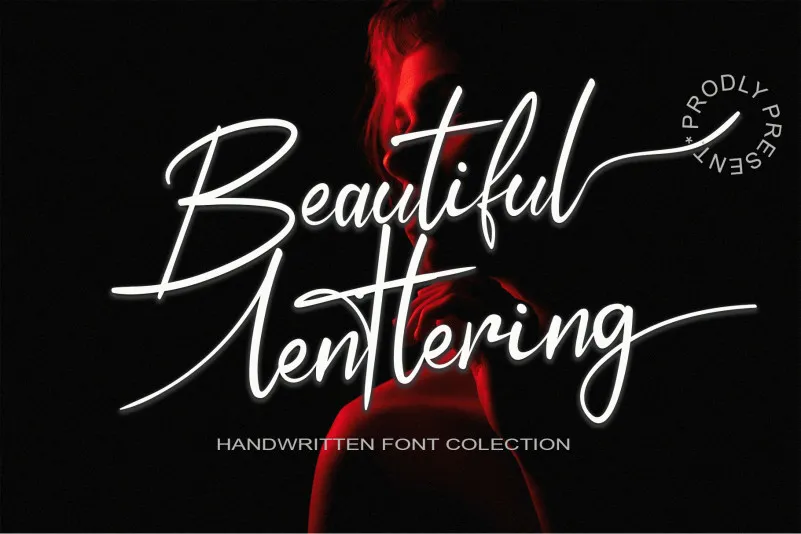
Beautiful Lenttering Font – Download Grátis
Esta é uma fonte script elegante com um clima contemporâneo e forma perfeita, inspirada em escrita clássica que resistiu ao tempo. Suave para os olhos, não é excessivamente fina nem grossa. Equilibrada e variada, foi projetada para aprimorar o encanto de seus trabalhos. Para quem busca uma fonte script com um toque elegante e moderno, esta fonte é perfeita. Ela combina delicadeza e força em sua proporção, mantendo-se fresca e inovadora sem perder o brilho tradicional do design literário. Ideal para projetos que exijam uma escrita fluida e sofisticada, a Beautiful Lenttering Font traz um toque de elegância ao seu trabalho, tornando-o ainda mais encantador e profissional.